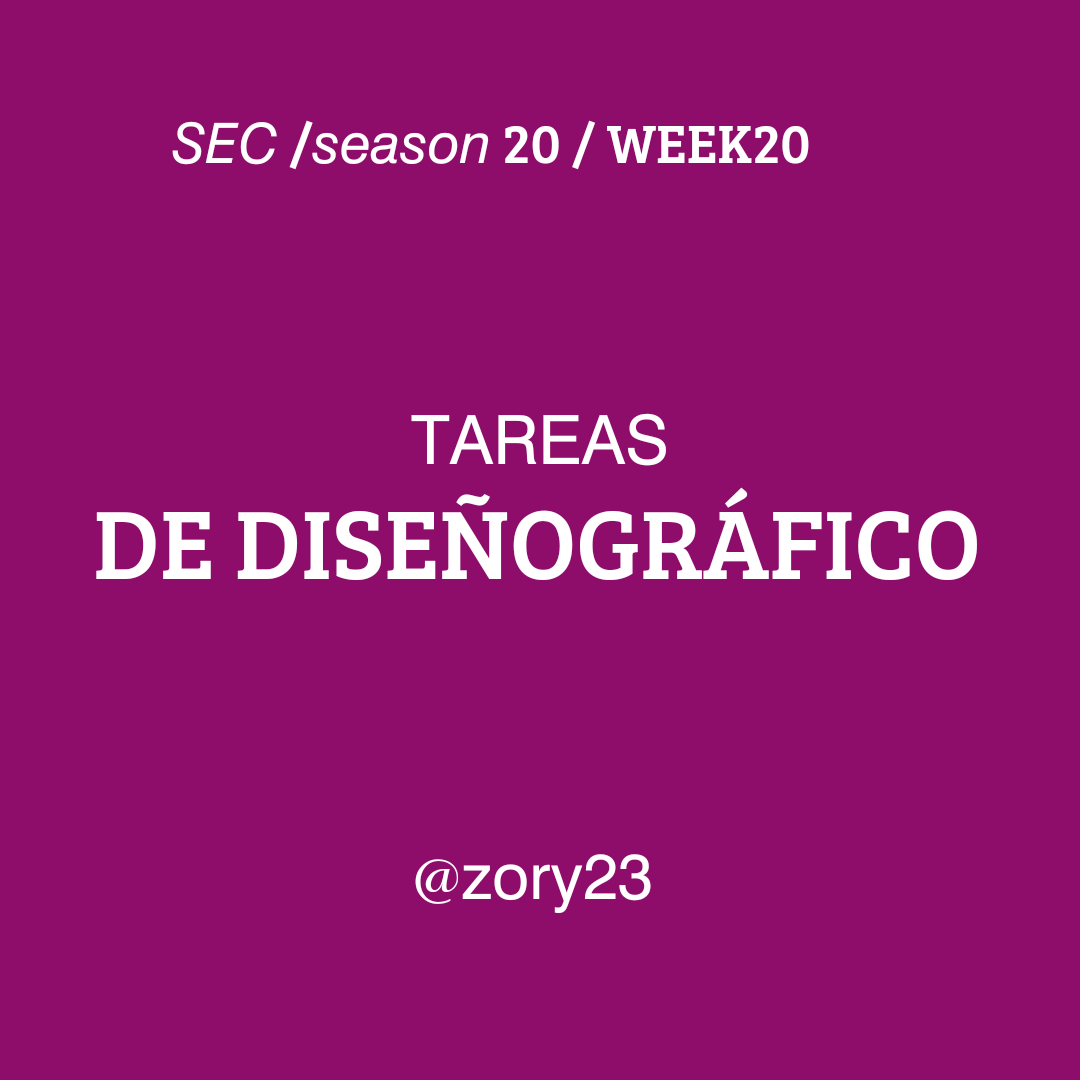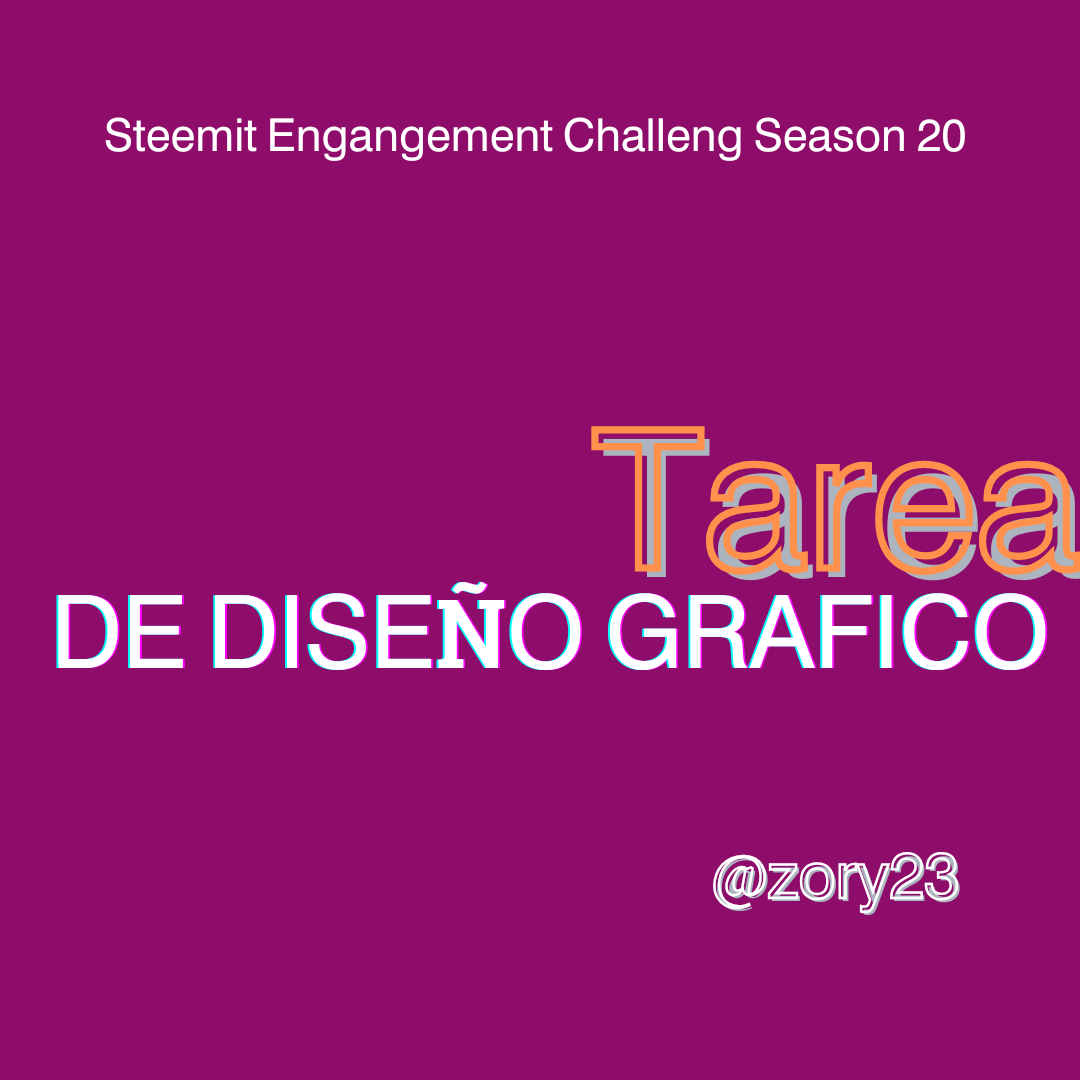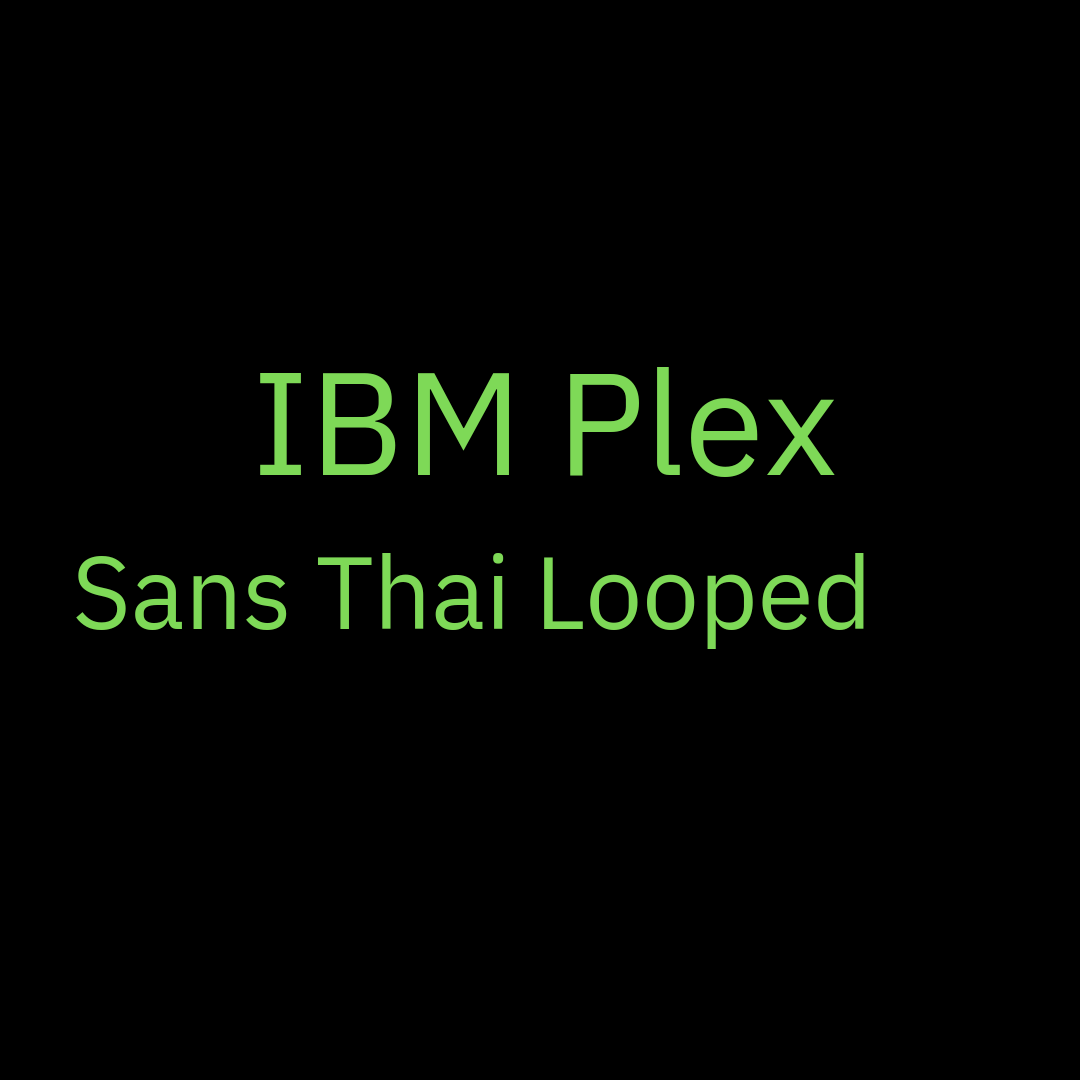
SEC20/WK3: Tipografía y aplicación práctica
Desde tiempos remotos la tipografía ha estado presente en la humanidad mediante la agrupación de un conjunto de símbolos, letras y puntos para dar forma a los mensajes que quiere transmitir.
• Discuta su comprensión sobre tipografía.
De acuerdo a lo investigado la Tipografía hace referencia a un arte donde se hace necesario la aplicación de pautas con el fin de crear mediante el uso de fuentes conformados en su conjunto por caracteres como letras con una gran infinidad de variantes, signos y números, con características comunes, que al ser agrupados de manera eficaz y poderosa plasman finalmente un mensaje con una variante de los tipos de letras especificas con la cualidad indispensable al momento de escribir y elaborar un diseño, antes de ser presentado constituyéndose en una valiosa herramienta imprescindible para comunicar en el diseño grafico.
• Investigue otras tres categorías de tipografías que no se hayan abordado en esta lección. Hable sobre ellas y proporcione una representación visual de las tipografías.
En el arte de la tipografía existen múltiples y diferentes categorías y entre las cuales se encuentran:
1- ☆-Display
Es clasificada como tipografía de decoración se dice que se hace difícil de categorizar y que esto se deba a que es de un diseño mas libre que implican estilos personales y para captar la mayor atención del espectador que la observe.
Permite Resaltar titulares y donde la legibilidad no sea prioritaria, es utilizada en casos de banners, en publicidad y logos, ya que reúne características únicas, que transmiten desenfado, originalidad, creatividad sin embargo dentro de las recomendaciones dadas es que no deben ser utilizadas en textos extensivos.
2- ☆-IBM Plex
Es un tipo de tipografía cuyo código es abierto tiende a competir con la Helvetica con respecto a su utilización, que refleja los valores y esencia como fundamento de la empresa que lleva su nombre, su diseño es realmente reciente y su diseñador fue Mike Abbink en el año 2017 y además posee en su haber 64 estilos que pueden ser descargados en la pagina principal de la marca mencionada.
3- ☆-Geomanis
Este tipo de tipografía, del grupo de las Sans se compone de letras mayúsculas geométricas y letras minúsculas similar a trazos hechos a mano, con retos secos y ligeramente condensados , pueden ser incluidos tanto en titulares como en el trazado de los textos.
• Demuestre su comprensión de la tipografía tal como lo hice con mis cuatro ejemplos utilizando las siguientes pautas a continuación.
a. Utilice “TAREAS DE DISEÑO GRÁFICO” como título principal
b.Utilice la combinación de colores que eligió en la tarea de esquema de colores de la semana pasada o cualquier otra diferente a la mía para demostrar
c.Asegúrate de crear 4 diseños (tipográficos) diferentes y resaltar los principios aplicados tal como lo hice yo.
DiseñoFuenteAlineacion
1-DiseñoBree Serif, IBM Plex Serif , Bree Serif y Gilda DisplayAlineación en el Centro
2-DiseñoSans Serif , Dm Serif Display, Bree SerifAlineación a la izquierda
3-DiseñoFlatory Serif, Monterchi Serif, Bree Serif, Dm Serif DisplayAlineación a la Izq
4-DiseñoDm Serif, Display, Bree, Serif, Dm Serif DidplayAlineación central, línea a izquierda, ultima línea a la derecha
d. Complete los detalles a continuación después de cada uno de los cuatro diseños utilizando esta tabla.
SNElementosRespuesta
1Tipografía de fuente utilizada:Arriba: Dm Serif Display, en el centro y nivel superior: Monterchi Serif y Bree Serif , abajo: Dm Serif Display
2Color hexadecimal utilizado:Fondo #8E0D6A, formas arriba y centro infrerior del marco: #FFDE59, centro inferior: #FFFFFF, abajo:#f3d768
3Alineación utilizadaArriba: ubicada al centro, línea media: esta a la derecha y abajo: alineada en el centro
SNElementosRespuesta
1.Tipografía/fuente utilizadaArriba; Bree Serif, primera linea intermedia; DM serif Display, segunda línea intermedia: fuente Bree Serif, fuente final, baja; DM Serif Display
2.Color hexadecimal utilizado:Fondo primario: Color hexadecimal numero #8E0D6A, fondo de la ubicación fuente superior; #001d1b, intermedia ; #000000, color fuente de la primera línea central: #ffffff, fondo fuente central de la segunda línea: #3ef3ff, color hexadecimal de la fuente inferior del diseño es el numero: #f5f1f1
3.Alineación utilizadaArriba Central, primera linea central superior; lado Izquierdo. Segunda línea central media; derecha, fuente final fue alineada a la derecha.
SNElementosRespuesta
1.Tipografía/fuente utilizada:Arriba: Adam Script, parte media superior; DM Serif Display, línea media inferios; Open Sans y abajo; DM Serif Display
2.Color hexadecimal utilizado:Fondo del diseño; #8e0d6, fondo superior donde se ubica la fuente es; #000000, fondo de doble color en la parte media del diseño; a) color Hexodecimal N° #ffffff y b) #fc6f17, línea media inferior también doble coloración; bordes con el color hexodecimal N° #fc6f17 y fondo; #181425, parte inferior del diseño; fondo de la fuente; #000000